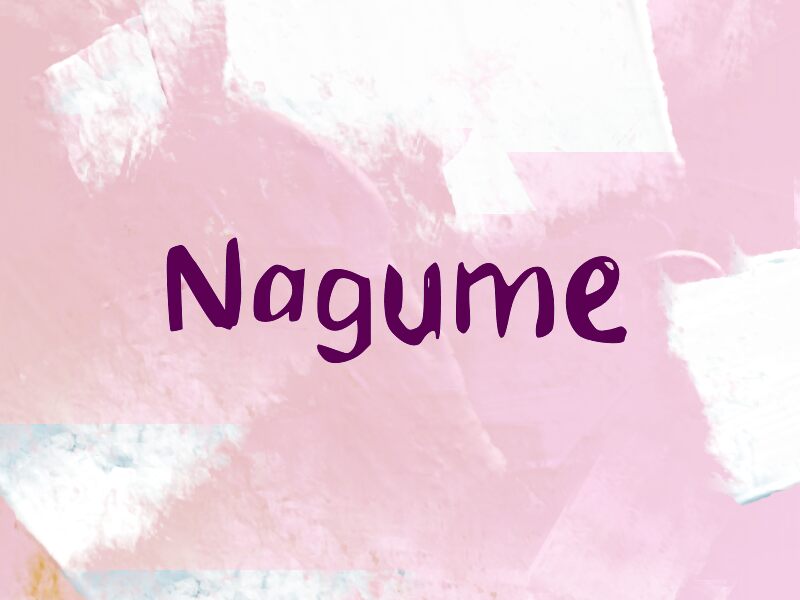
Nagume, une police brush gratuite créée par Wep, affiche une esthétique manuscrite décontractée. Ses courbes douces et ses traits légèrement irréguliers lui confèrent un aspect humain et authentique. Les lettres suivent un rythme naturel, mêlant formes arrondies, jointures fuselées et quelques angles vifs, pour un rendu vivant plutôt que trop lisse.
C’est ce qui rend Nagume parfaite pour l’identité visuelle de cafés, les affiches, les couvertures de livres, le packaging ou les réseaux sociaux : une police gratuite qui apporte de la chaleur sans tomber dans l’effet « mignon » ou enfantin. Elle est particulièrement efficace pour les phrases courtes, les titres et les logos, car ses formes larges au pinceau et son espacement dynamique donnent une présence artisanale, presque tactile, même aux mots les plus simples.